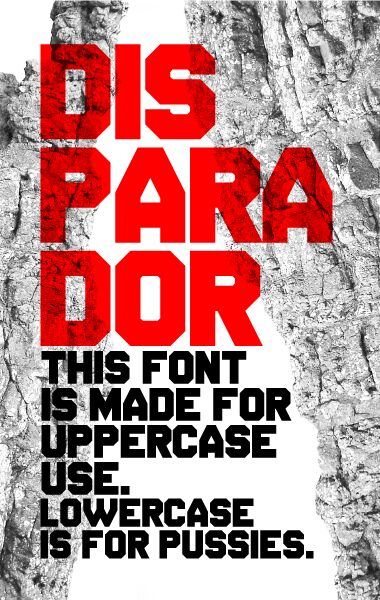
Disparador, který navrhl Tobias Sommer, je bezplatné techno display písmo složené z pevných geometrických tahů, ostrých pravých úhlů a ostře řezaných rohů. Obdélníkové mezery dodávají písmenům přesnou, strojovou strukturu.
Digitální grafika je jeho nejpřirozenějším prostředím, protože opakující se zářezy a čtvercové spoje mohou připomínat panely rozhraní, herní nabídky a plakáty na akce elektronické hudby bez nutnosti použití dalších efektů. Stejná hranatá konstrukce může utvářet obaly a branding pro herní hardware, audio zařízení nebo softwarové produkty a mění název v kompaktní znak, který vypadá, jako by byl přímo součástí samotného výrobku, nikoli jen jako běžný tištěný text.